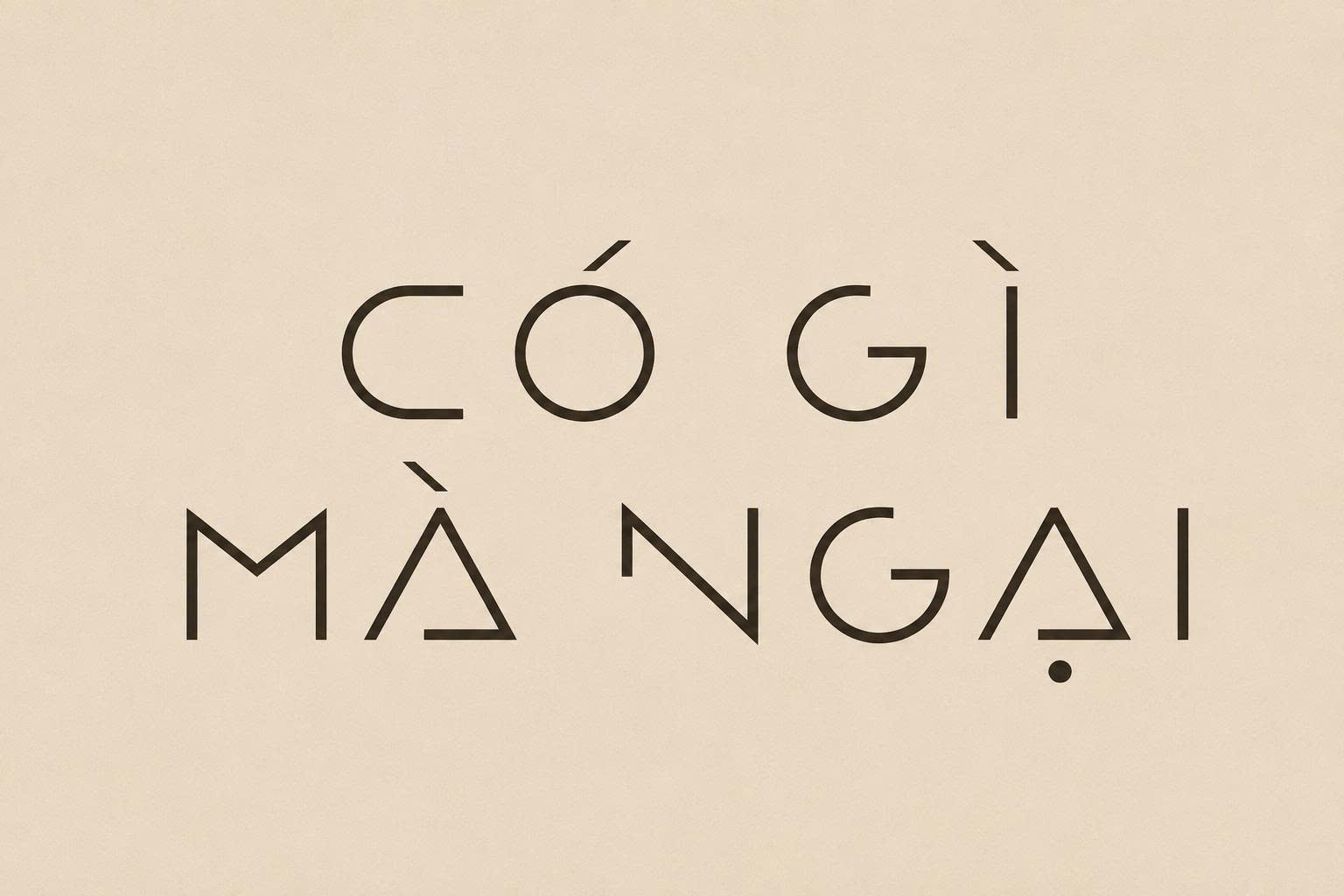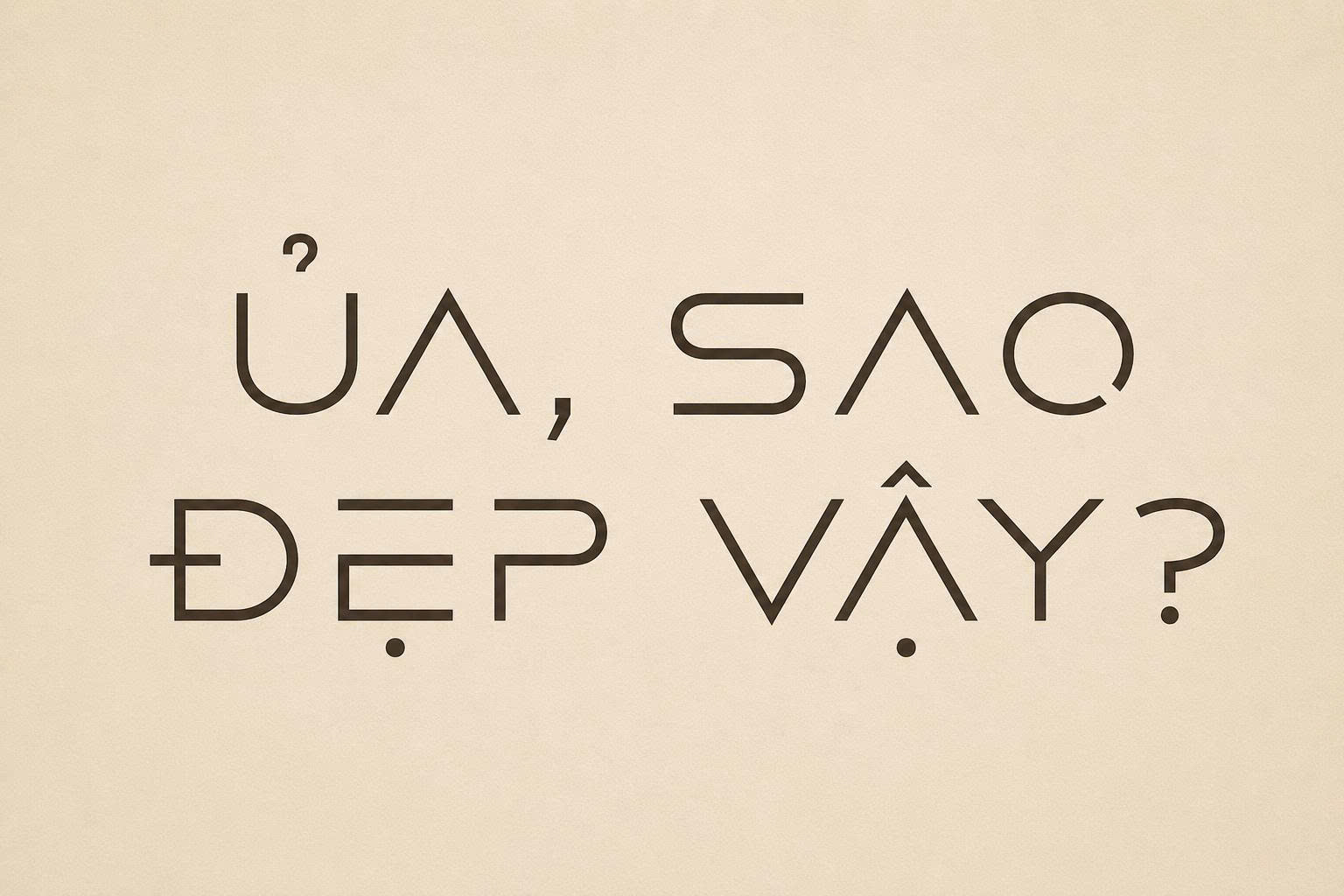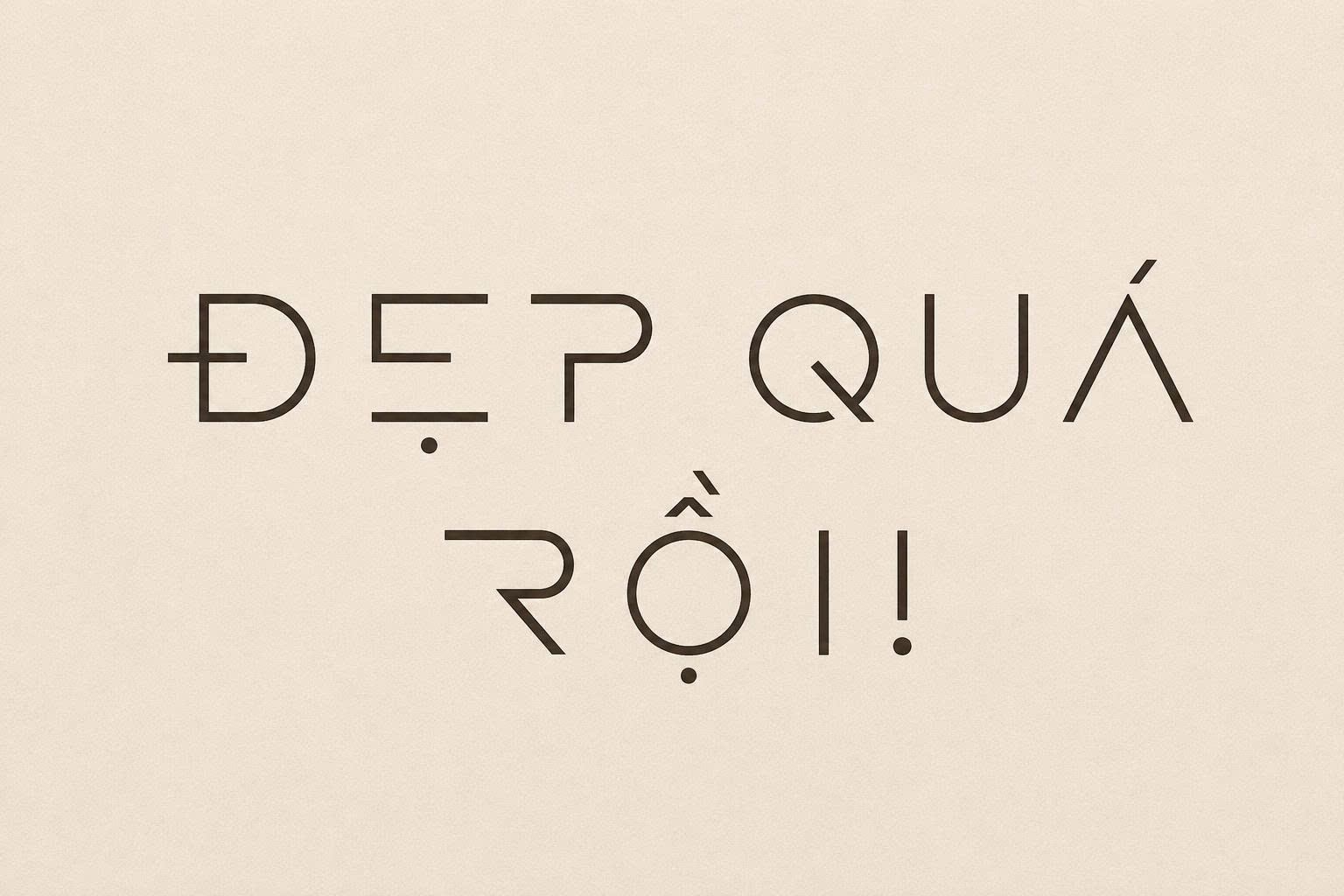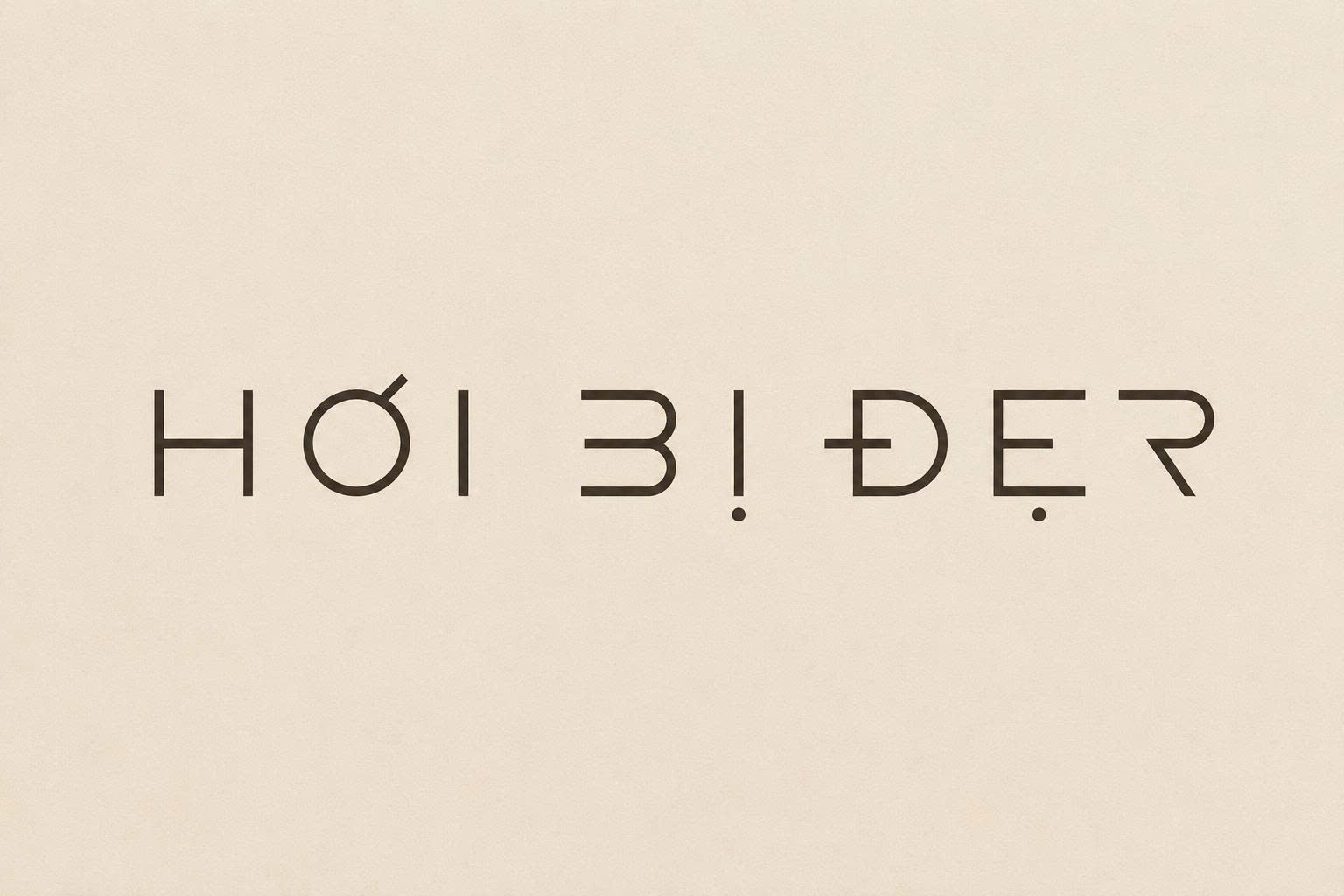
Font Flux Architect Việt hóa là bộ phông chữ viết tay kỹ thuật mang phong cách đặc trưng của các bản vẽ kiến trúc và thiết kế xây dựng. Với cấu trúc nét chữ dứt khoát, sạch sẽ và có độ nghiêng nhẹ tự nhiên, Flux Architect mang lại vẻ ngoài vừa chuyên nghiệp, vừa mộc mạc cho các dự án thiết kế. Doozypack.vn cung cấp link tải font Flux Architect Việt hóa chuẩn, giúp bạn sở hữu bộ font Flux Architect tiếng Việt không lỗi dấu thanh để hiện thực hóa các bản vẽ, tiêu đề bao bì hoặc nhận diện thương hiệu cho các studio sáng tạo.
Đặc điểm thẩm mỹ của font Flux Architect Việt hóa
Flux Architect không chỉ đơn thuần là một bộ phông chữ viết tay; nó mô phỏng chính xác thói quen ghi chú của các kiến trúc sư trên bản vẽ Blueprint truyền thống.
Phong cách Handwriting kỹ thuật và chuẩn xác
Đặc trưng lớn nhất của font Flux Architect Việt hóa là sự kết hợp giữa nét vẽ tay ngẫu hứng và sự kỷ luật của dân kỹ thuật. Các ký tự có độ cao đồng nhất, nét chữ mảnh nhưng rõ ràng, tạo cảm giác như được viết bằng bút kim chuyên dụng trên giấy can. Phong cách này giúp bản thiết kế của bạn toát lên sự tỉ mỉ, sáng tạo và đầy tính chuyên môn.
Hệ thống dấu tiếng Việt được tinh chỉnh hài hòa
Nỗi đau của các designer khi sử dụng font Flux Architect bản gốc là các dấu thanh (sắc, huyền, hỏi, ngã, nặng) thường bị nhảy font hoặc sai lệch kích thước so với thân chữ. Phiên bản Việt hóa tại Doozypack.vn đã được tối ưu hoàn toàn. Các bộ dấu được thiết kế với độ dày nét tương đồng, đảm bảo văn bản tiếng Việt luôn cân đối và giữ nguyên tinh thần “phác thảo” độc đáo của bộ font.
Tại sao designer nên chọn font Flux Architect tiếng Việt cho dự án?
Trong ngành thiết kế đồ họa và sản xuất bao bì tại Doozypack.vn, Flux Architect được ưa chuộng nhờ tính ứng dụng thực tế cao:
- Tạo dấu ấn cá nhân và sáng tạo: Rất phù hợp cho các thương hiệu muốn nhấn mạnh quy trình thiết kế thủ công hoặc các sản phẩm có tính chất tư vấn kiến trúc, nội thất.
- Độ dễ đọc tuyệt vời: Khác với các dòng font script uốn lượn, Flux Architect có cấu trúc chữ in hoa (Caps) rõ ràng, giúp thông tin hiển thị sắc nét ngay cả ở kích thước nhỏ.
- Giải quyết bài toán đồng bộ: Việc sử dụng bản Việt hóa giúp bạn thống nhất phong cách từ bản vẽ kỹ thuật đến nhãn mác sản phẩm và tài liệu truyền thông.
- Bao bì phụ kiện & Công cụ: Rất phù hợp cho tên sản phẩm trên vỏ hộp đinh vít, dụng cụ cầm tay hoặc bộ kit lắp ráp, tạo cảm giác chuyên nghiệp.
- Hộp đựng sản phẩm nội thất: Dùng cho nhãn dán hoặc hướng dẫn lắp đặt in trực tiếp lên vỏ hộp Carton, giúp thông tin trông như một bản vẽ kỹ thuật thực thụ.
- Tem nhãn sản phẩm Handmade: Kết hợp cùng giấy Kraft nâu để tạo phong cách mộc mạc, thô sơ nhưng đầy tính nghệ thuật.
- Túi giấy văn phòng kiến trúc: Tên công ty in bằng font Flux Architect giúp khẳng định gu thẩm mỹ đặc thù của ngành nghề xây dựng.